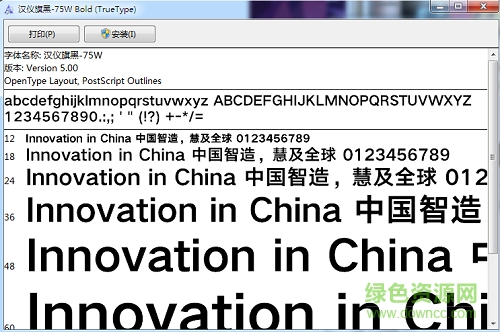
hyqihei gew字體又稱(chēng)漢儀旗黑75w字體,是漢儀旗黑系列中的一款,字體線(xiàn)條勁道,緊致,簡(jiǎn)潔勻質(zhì)硬朗,整體看起來(lái)非常的養(yǎng)眼,有喜歡這款字體的朋友歡迎下載使用!
hyqihei gew是一款設(shè)計(jì)簡(jiǎn)約、爽朗富有時(shí)代氣息,筆畫(huà)設(shè)計(jì)中融入了書(shū)寫(xiě)的韻味,采用“陰陽(yáng)線(xiàn)”的處理方法,講究線(xiàn)條之美,使筆劃挺拔有力,剛?cè)嵯酀?jì),通過(guò)筆畫(huà)的粗細(xì)變化,賦予字體不同的性格與表現(xiàn)力!